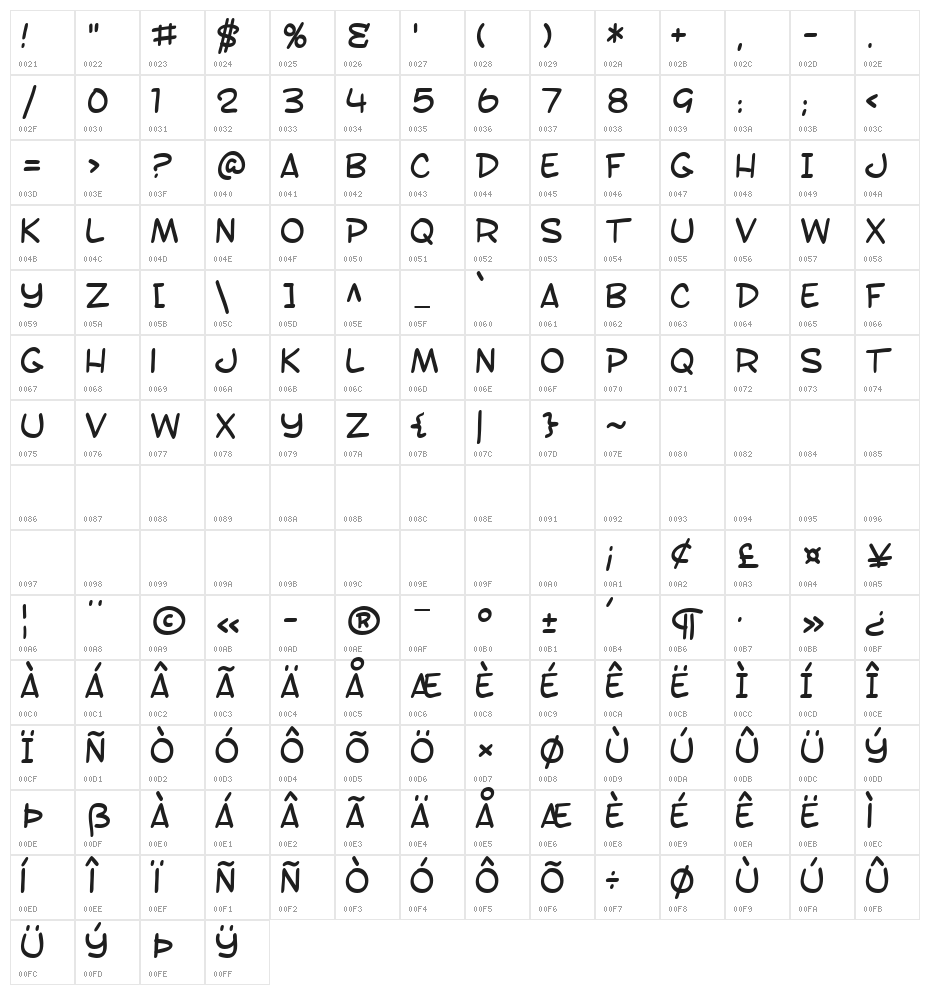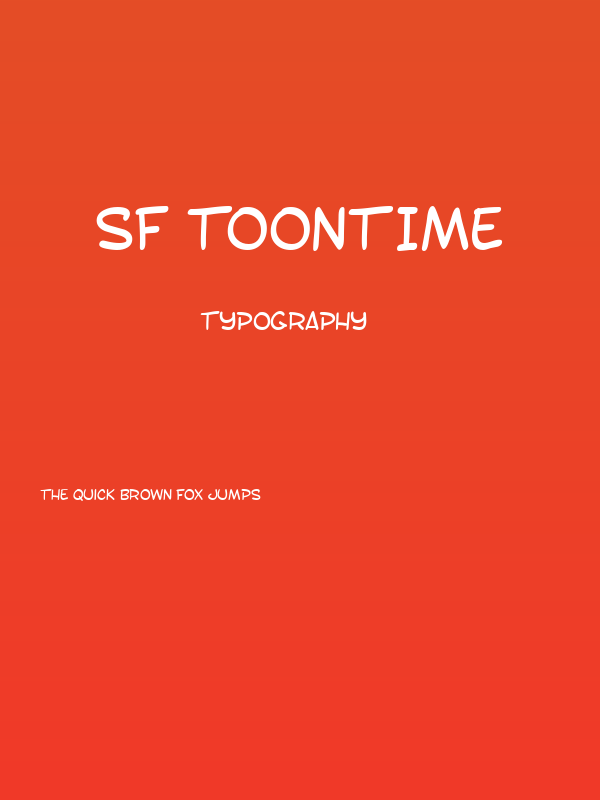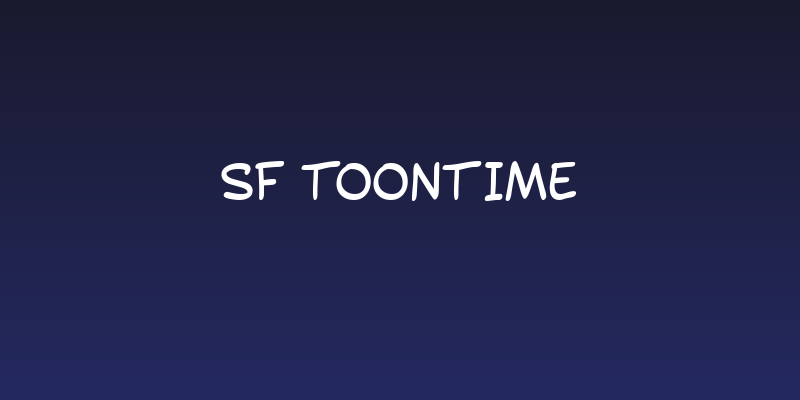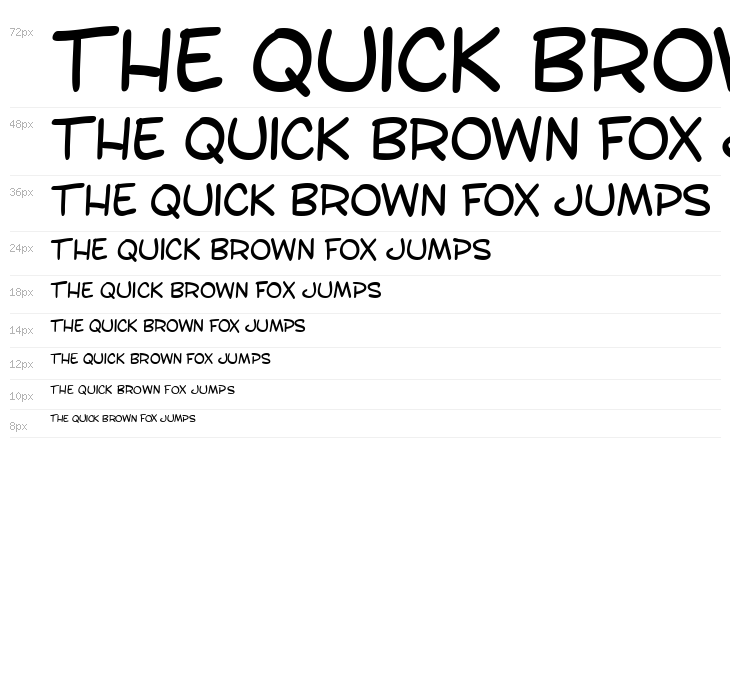
SF Toontime Font
| Stile generale | Whimsical |
| Progetti proposti | Ideal for children's books, comic strips, playful branding, and casual invitations. |